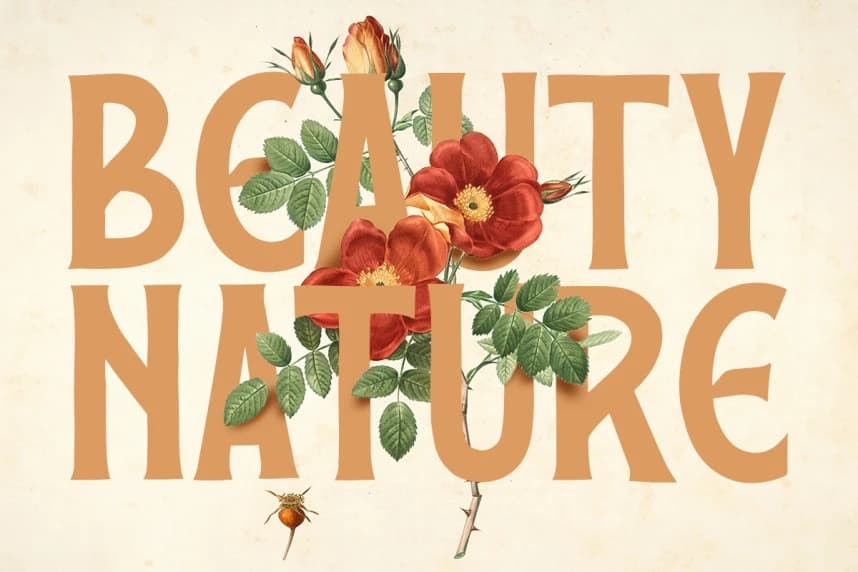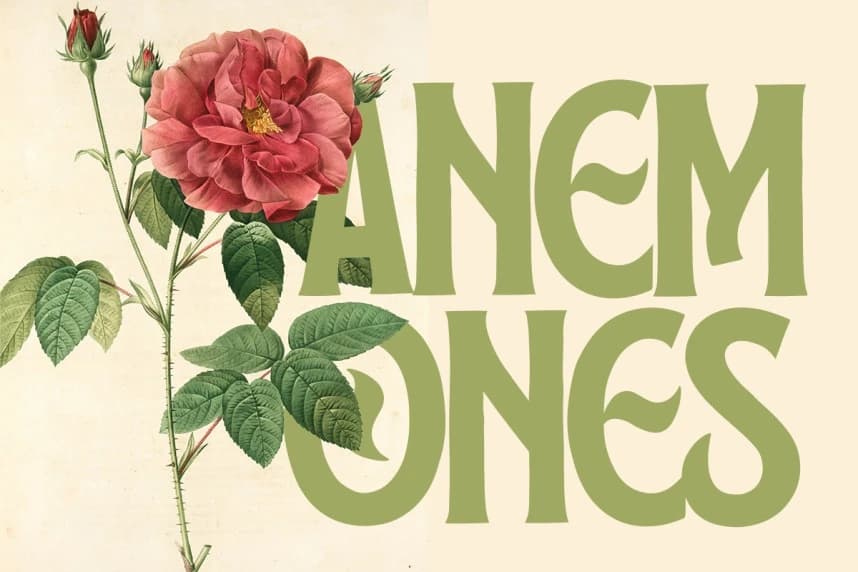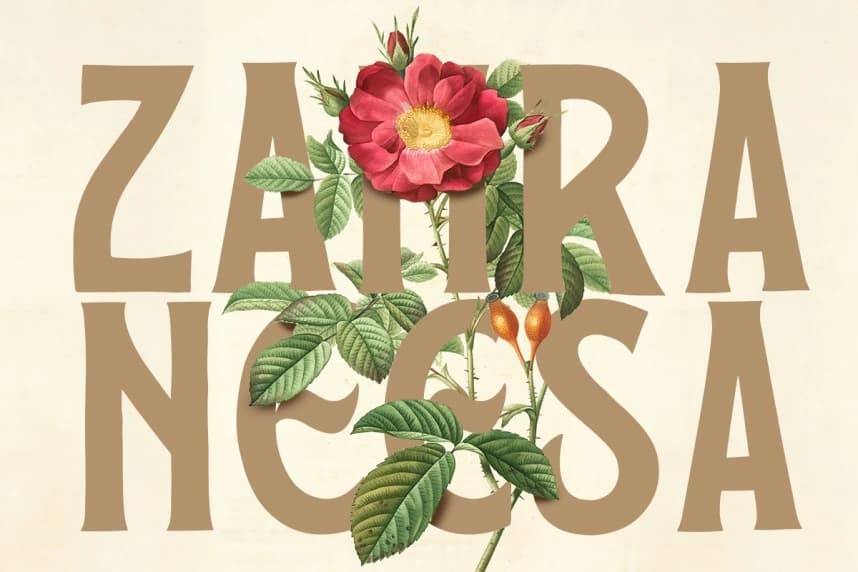
Shade Font
Shade Font A Modern Display Font Adından da anlaşılacağı gibi Shade A Modern Display Font, güzellik yayan ve en zarif yazı tiplerinden biridir. Okunması kolay, aynı zamanda sanatsal olan bu yazı tipi, kullanıcıya bağlı olarak çeşitli amaçlar için kullanılabilir.
Shade Font A Modern Display Font, isminin gösterdiği gibi, zarafet yayan ve en zarif yazı tiplerinden biridir. Okunması kolayken aynı zamanda sanatsal olan bu yazı tipi, kullanıcıya bağlı olarak birden çok kullanım alanı sunabilir.